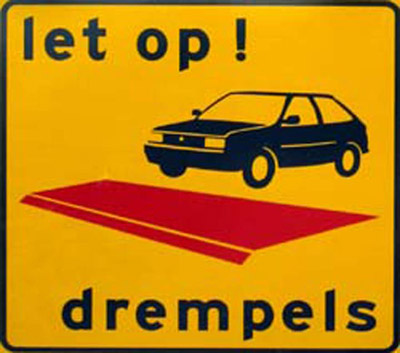
Suche Font: Niederländische Straßenschilder "Let op Drempels"
da ich nun schon viele Male in den Niederlanden war und sehr von deren Designvielfalt überwältigt bin, möchte ich mich gerne näher mit "typisch Holländischen Schriften" beschäftigen. Dafür suche ich nun schon 2 Stunden nach dem Namen des Fonts auf dem sehr bekannten Straßenschild "Let op Drempels" :)
Auch gerne würde ich wissen, wie die Schrift auf den Autobahnschildern in Holland heißt - das ist aber nur Secundär. Wichtig ist mir, den Namen der Schrift auf dem folgenden Bild rauszufinden:
ich schätze, dass das eine etwas in die Breite verzerrte Interstate ist. Unser Forums-Chef Ralf kann Dir zu dem Thema aber bestimmt noch deutlich mehr sagen als ich. :-)
Das ist die »alte« niederländische Schilderschrift, die auf der amerikanischen FHWA-Serie beruht.
In der Regel laufen die unter der Bezeichnung »ANWB«, wobei es verschiedene Schnitte gibt ANWB-Ee, ANWB-Cc …
ANWB ist eine Verkehrsorganisation, die aber die Schilder nicht mehr exklusiv fertigt. Daher gibt es auch RWS-Ee, was dann wiederum für Rijkswaterstaat steht.
Neuer ist die ANWB-Uu von Gerard Unger, die aber hier in dem Bild nicht verwendet wurde.